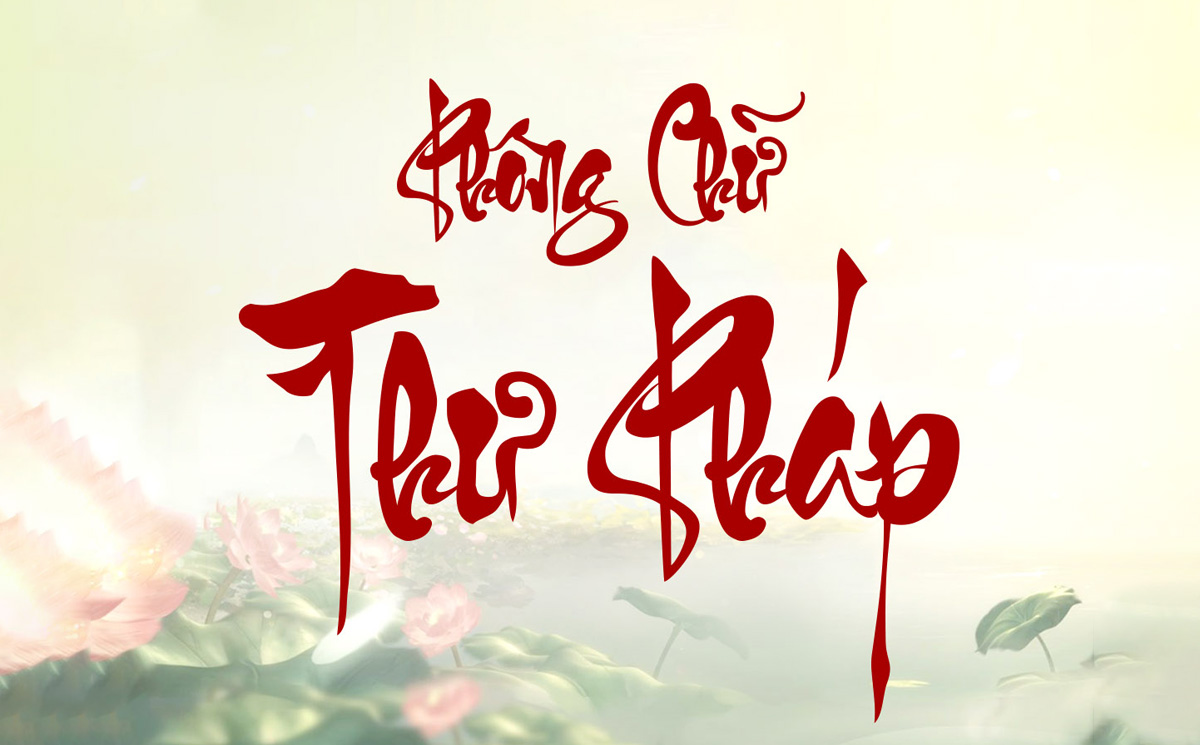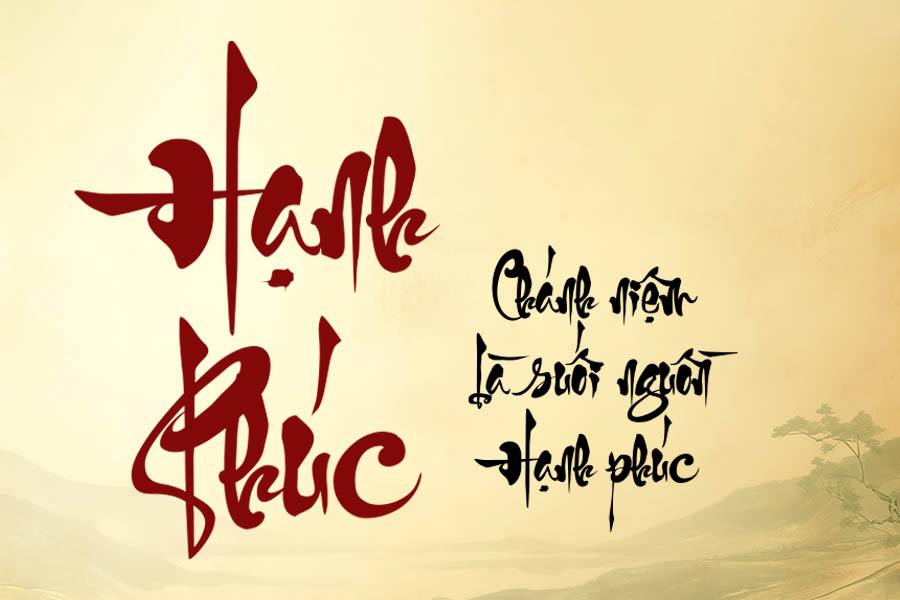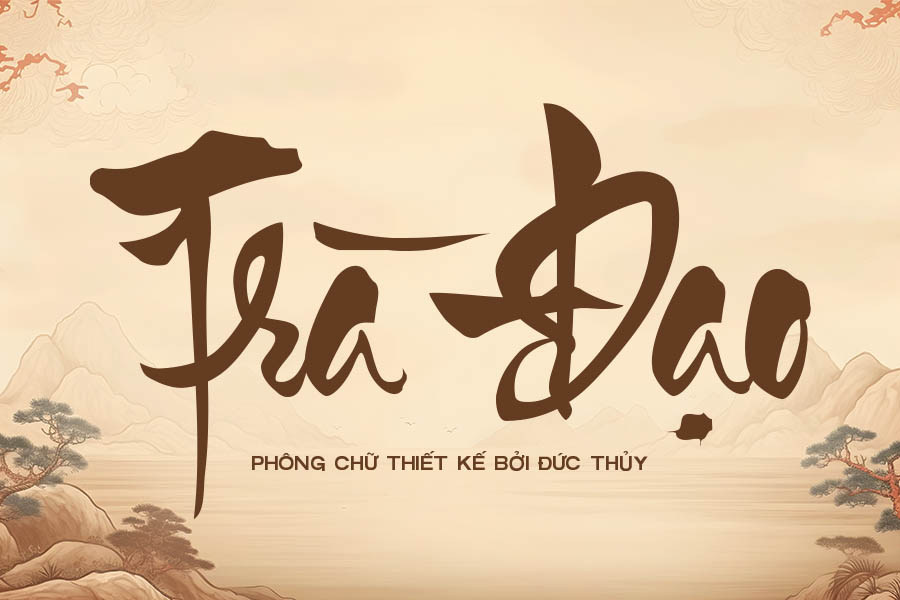
Font Chữ Thư Pháp Đức Thủy - Font Chữ Tiếng Việt
Bạn đang tìm một font chữ thư pháp đậm chất Việt, mang phong cách mềm mại, nghệ thuật và uyển chuyển? Bộ font thư pháp Đức Thủy là một lựa chọn không thể bỏ qua – không chỉ bởi nét chữ tinh tế mà còn vì nó được tạo nên từ tâm huyết của một người yêu chữ Việt: Đức Thủy – Admin Font Zin.
Giới thiệu font chữ thư pháp Đức Thủy
Font chữ thư pháp Đức Thủy thuộc nhóm font nghệ thuật kiểu viết tay thư pháp, được thiết kế dành riêng cho các ứng dụng sáng tạo mang hơi hướng truyền thống: như câu đối Tết, thiệp chúc, bìa sách văn học, hay các dự án mang đậm bản sắc văn hóa Việt.
Bộ font tái hiện rất chân thực phong cách thư pháp Việt, với nét lượn mềm mại, dày mỏng linh hoạt.
Tác giả thiết kế – Niềm đam mê từ cộng đồng Font Zin
Font được sáng tạo bởi Đức Thủy ADmin Fontzin – một trong những nhóm chia sẻ font Việt hóa tích cực và uy tín tại Việt Nam.
Với tinh thần tôn vinh chữ viết và giữ gìn giá trị văn hóa, Đức Thủy không chỉ đơn thuần số hóa chữ viết tay, mà còn truyền tải tinh thần thư pháp truyền thống vào từng nét bút. Font không rập khuôn, không máy móc, mà mang hơi thở thủ công – rất phù hợp với thiết kế hiện đại mang dấu ấn văn hóa.
Font chữ thư pháp Đức Thủy phù hợp với ai?
• Những bạn làm thiết kế đồ họa truyền thống như: thiệp Tết, banner mừng xuân, pano, backdrop…
• Nghệ sĩ chữ viết, làm typographic art mang tính cổ truyền hoặc hiện đại kết hợp
• Các nhà xuất bản, giáo viên dạy văn hóa Việt hoặc nhà nghiên cứu muốn tạo điểm nhấn thẩm mỹ trong tài liệu giảng dạy
• Những ai đang làm sản phẩm văn hóa, du lịch, sản phẩm lưu niệm Việt Nam
Tổng kết
Font thư pháp Đức Thủy không chỉ là một bộ font nghệ thuật – nó còn là một tuyên ngôn tinh tế về cái đẹp, sự mềm mại và tâm hồn Việt trong từng nét chữ.
Nếu bạn đang tìm kiếm một font chữ thư pháp mang hồn dân tộc, nhưng vẫn có tính ứng dụng cao trong thiết kế hiện đại, thì đây chính là lựa chọn bạn nên thử.